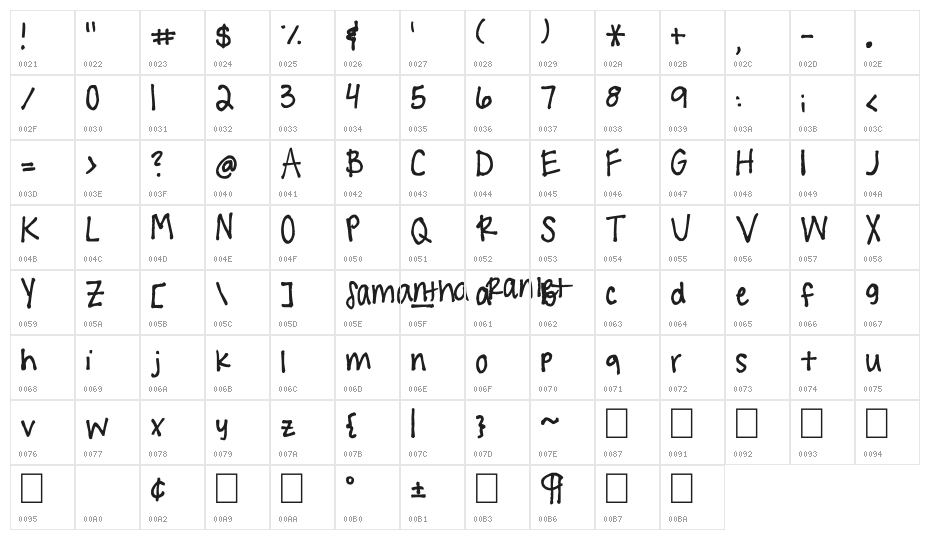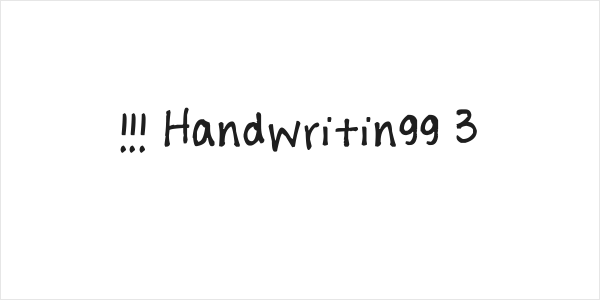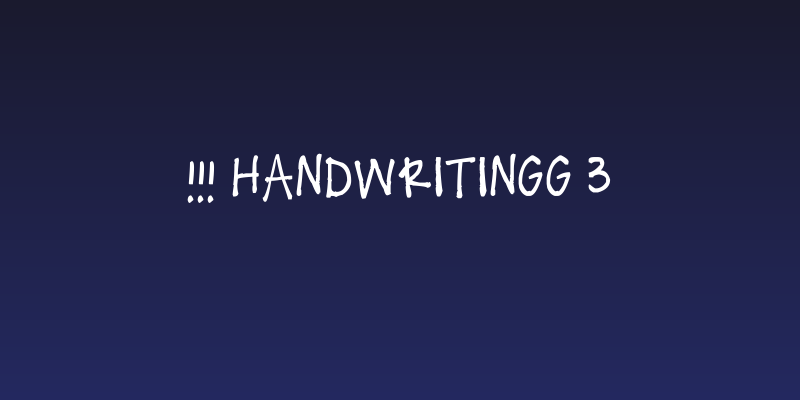
!!! Handwritingg 3 Font
| Gesamtstil | Casual |
| Anwendungsfall | Headlines, Logos, Creative projects |
| Vorgeschlagene Projekte | Ideal for greeting cards, children's books, personal blogs, and creative branding projects. |